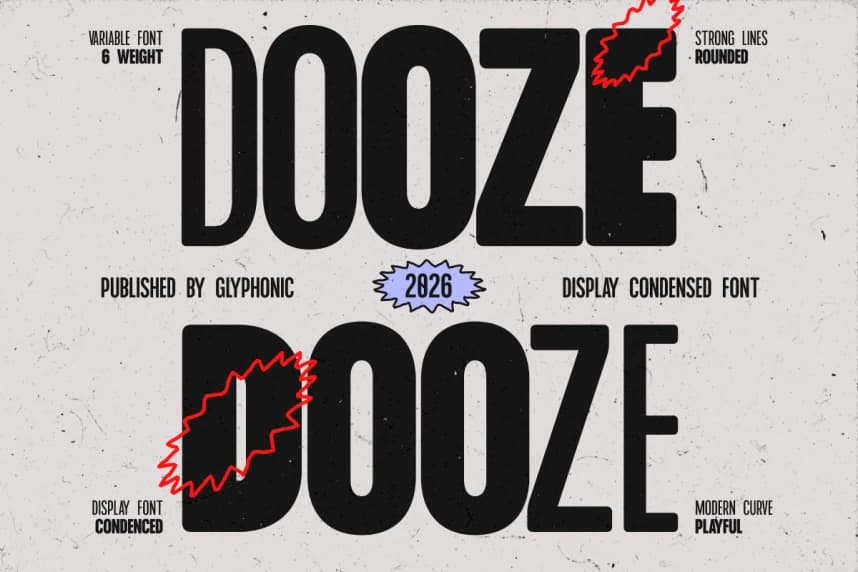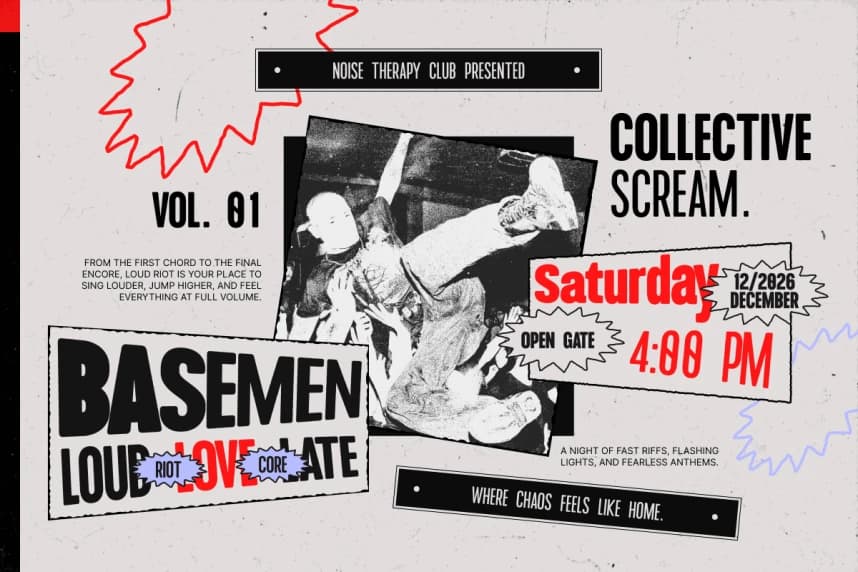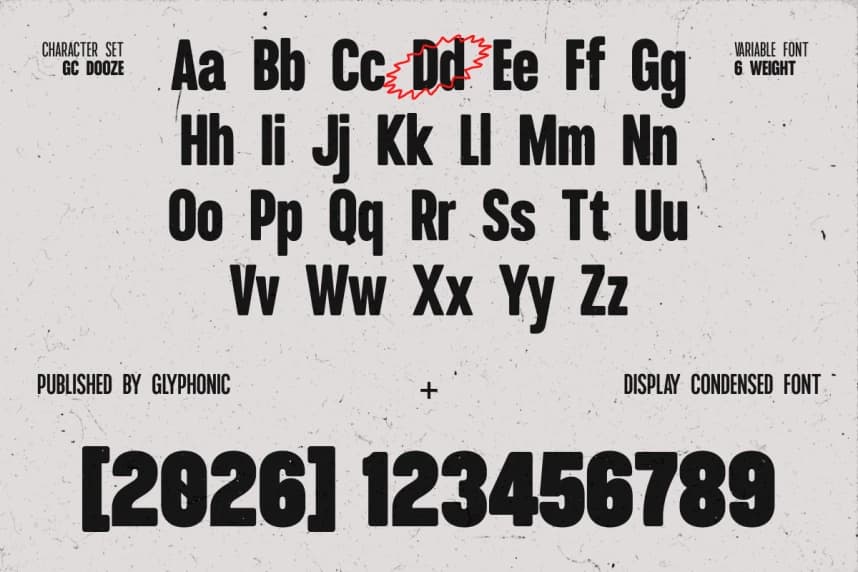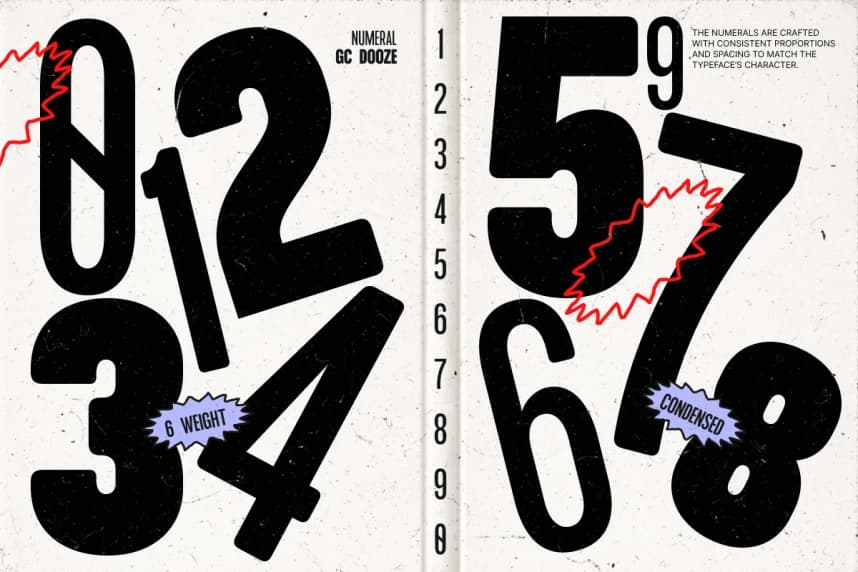
GC Dooze – Display Condensed Sans Font
GC Dooze - Display Condensed Sans Font, güçlü dikey yapıyı akıcı yuvarlak kenarlarla birleştiren cesur sıkıştırılmış bir yazı tipidir ve güç ile oyun arasındaki belirgin bir denge yaratır. Yükselip ayakta durması ve dikkat çekmesi için tasarlanan Dooze, çarpıcı bir görsel varlık sunar ve aynı zamand
GC Dooze - Display Condensed Sans Font, güçlü bir sıkıştırılmış yazı tipi olup, güçlü dikey yapı ile pürüzsüz yuvarlak kenarları bir araya getirerek güç ile neşeli oyun arasında belirgin bir denge yaratır. Dooze, dik durması ve dikkat çekmesi için tasarlandığından çarpıcı bir görsel varlık sunar ve aynı zamanda dostane ve modern bir ton korur.